Как дозировать экспериментальную гарнитуру в фирменной графике
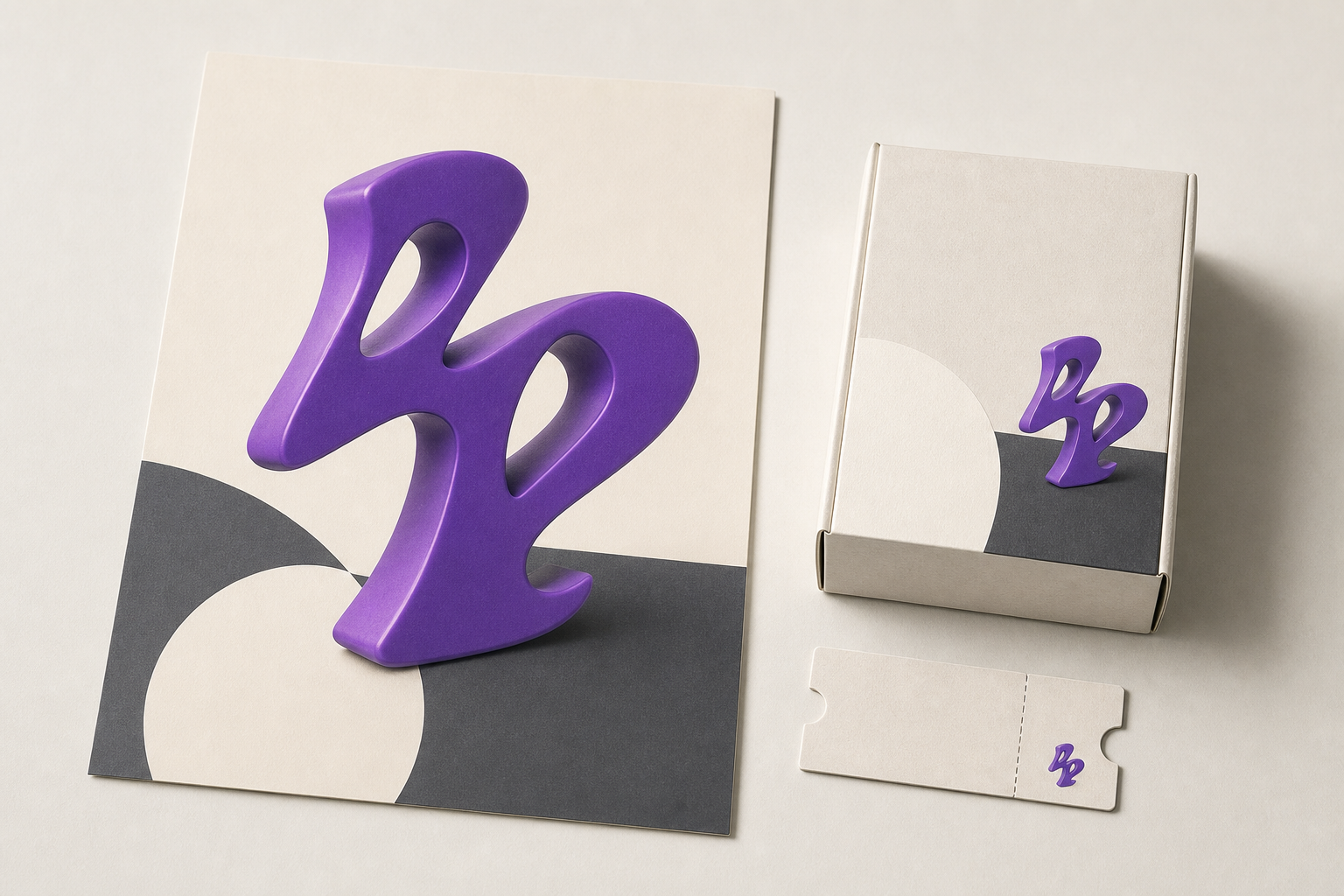
Экспериментальную гарнитуру в фирменной графике лучше использовать как управляемый акцент, а не как универсальный шрифт для всех текстов. Сначала определите её роль в айдентике, затем ограничьте области применения, настройте иерархию и проверьте читаемость на реальных носителях — от упаковки до мобильного экрана.
Что такое дозировка экспериментального шрифта
Дозировка экспериментальной гарнитуры — это не фиксированный процент её присутствия в макете, а система ограничений. Она определяет, где необычный шрифт появляется, какого размера используется, сколько текста им набирается и какие функции выполняет. В результате гарнитура остаётся заметной, но не конкурирует с содержанием и не превращает каждый элемент бренда в визуальный шум.
Экспериментальной можно считать гарнитуру с нестандартной пластикой букв, необычной шириной, резким контрастом штрихов, нестандартными пропорциями или декоративными формами. Такая типографика хорошо передаёт характер: технологичность, дерзость, культурную смелость, игровое настроение или премиальную дистанцию. Однако выразительность шрифта почти всегда снижает универсальность, поэтому его роль нужно проектировать заранее.
Начните с роли гарнитуры в айдентике
До выбора размера и сочетаний ответьте на вопрос: какую задачу решает экспериментальная гарнитура? Если она только создаёт визуальный импульс, ей подходят короткие заголовки и акцентные слова. Если она является главным носителем характера бренда, можно расширить применение, но оставить нейтральную гарнитуру для длинного текста, навигации и служебной информации.
Акцентный голос
Акцентный голос используется в названиях кампаний, заголовках плакатов, обложках, коротких слоганах и отдельных словах. Это самый безопасный сценарий: нестандартная форма получает достаточно пространства, а читатель быстро считывает сообщение. Для такого режима особенно важны крупный кегль, свободное поле и короткая фраза без сложных переносов.
Системный маркер
Системный маркер появляется в повторяющихся элементах: названиях рубрик, номерах коллекций, навигационных метках, стикерах или выделениях внутри макета. Здесь шрифт работает как узнаваемый сигнал. Его применение должно быть стабильным: одинаковые элементы получают одинаковую роль, иначе фирменная типографика будет выглядеть случайным набором эффектов.
Основной фирменный шрифт
Иногда экспериментальная гарнитура становится полноценным фирменным шрифтом. Это оправдано, если у неё есть рабочие начертания, понятная кириллица, достаточная различимость знаков и версии для разных размеров. Даже в этом случае полезно назначить ей зоны применения: дисплейные начертания для крупных форматов, более спокойные варианты для коротких текстов и отдельный нейтральный шрифт для функциональных сообщений.
Выберите уровень присутствия на носителях
Вместо абстрактного правила «использовать умеренно» составьте карту носителей. Один и тот же шрифт может быть доминирующим на афише, второстепенным на упаковке и почти незаметным в интерфейсе. Дозировка зависит от расстояния чтения, длительности контакта с сообщением, количества текста и цены ошибки при непонимании.
Постройте типографическую иерархию
Фирменная графика становится убедительной, когда читатель понимает порядок чтения. Экспериментальная гарнитура должна занимать конкретный уровень иерархии: например, первый — для заголовка, второй — для подзаголовка, третий — для пояснения. Не позволяйте необычному шрифту одновременно быть заголовком, подписью, кнопкой и мелкой служебной строкой: одинаковая пластика на всех уровнях стирает приоритеты.
Практичная схема состоит из трёх ролей. Первая гарнитура привлекает внимание и задаёт настроение. Вторая обеспечивает чтение основного текста и интерфейсных элементов. Третьим инструментом могут стать цвет, размер, регистр, интервалы или графический знак. Такая система не требует большого количества шрифтов: характер создаётся контрастом функций, а не количеством декоративных решений.
Проверяйте не только кегль, но и плотность
Крупный размер не гарантирует хорошую читаемость. На восприятие влияют ширина строки, межбуквенное расстояние, высота строки, насыщенность и соседство с другими объектами. Узкая гарнитура может выглядеть эффектно в одном слове, но утомлять в предложении. Плотный рисунок букв требует больше воздуха, а сложные формы — более коротких текстовых фрагментов.
Сочетайте экспериментальный шрифт с нейтральным
Нейтральный партнёр нужен не для того, чтобы сделать дизайн незаметным, а чтобы распределить нагрузку. Он принимает на себя длинные абзацы, подписи, таблицы, адреса, цены и интерфейсные команды. В паре с выразительной гарнитурой нейтральный шрифт должен быть достаточно самостоятельным для чтения, но не настолько характерным, чтобы возникло соперничество.
Ищите контраст функций, а не случайную непохожесть
Хорошая шрифтовая пара строится на различии задач и согласованности ритма. Сравните высоту строчных знаков, ширину, насыщенность, форму круглых букв, характер цифр и поддержку кириллицы. Если экспериментальная гарнитура широкая и тяжёлая, партнёру не обязательно быть противоположностью во всём: важнее, чтобы он спокойно набирал текст и сохранял нужный ритм строк.
Экспериментальная гарнитура работает лучше всего, когда у неё есть ясная роль, ограниченная зона применения и надёжный текстовый партнёр. Определите иерархию, протестируйте кириллицу и реальные носители, зафиксируйте правила — так выразительный шрифт станет частью цельной айдентики, а не случайным декоративным эффектом.